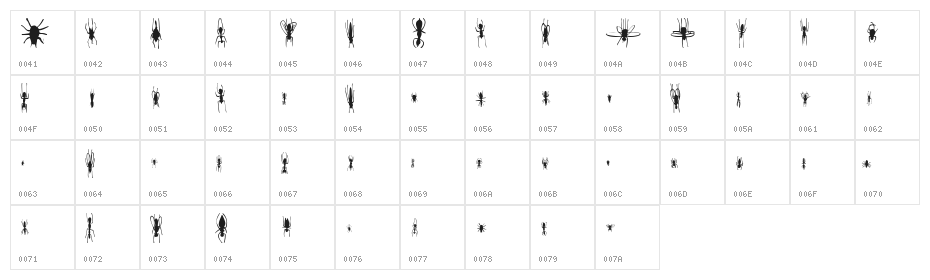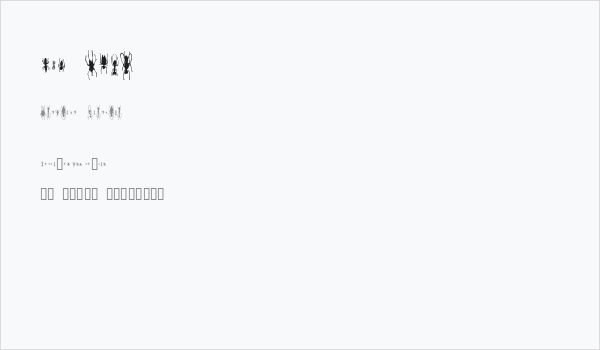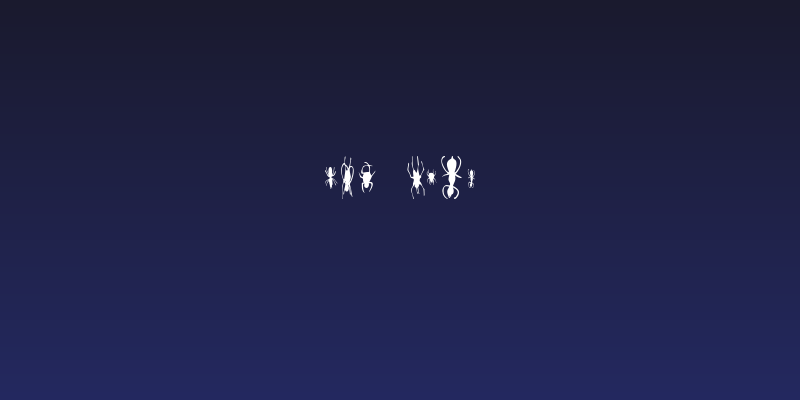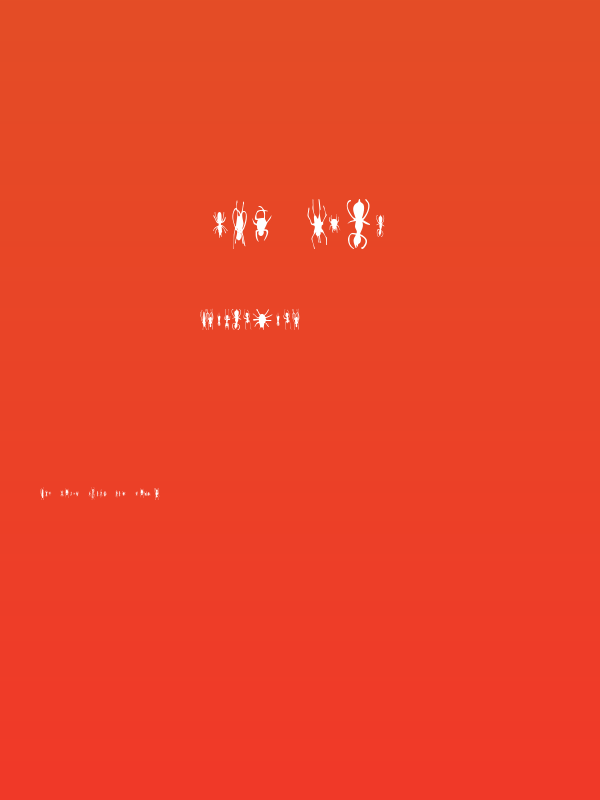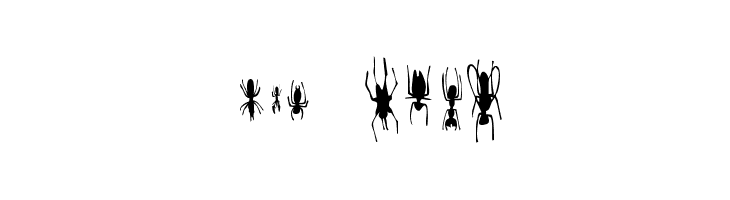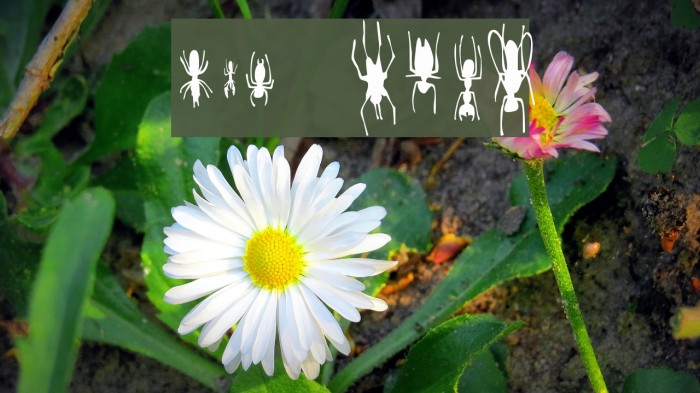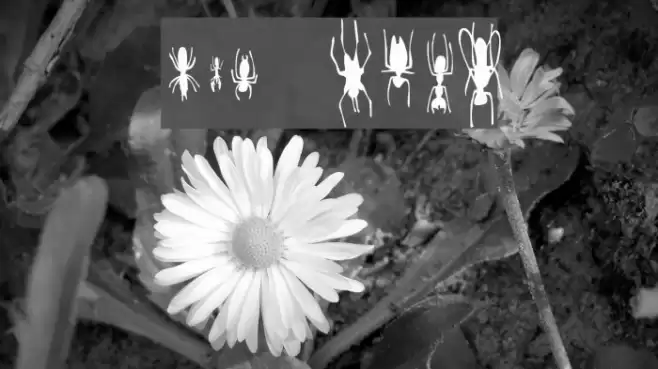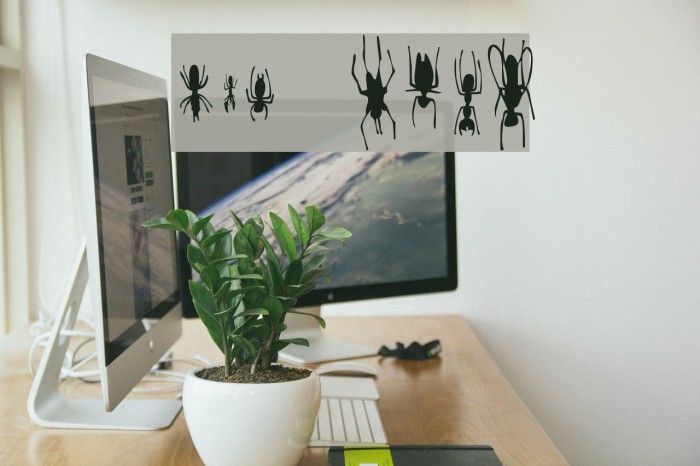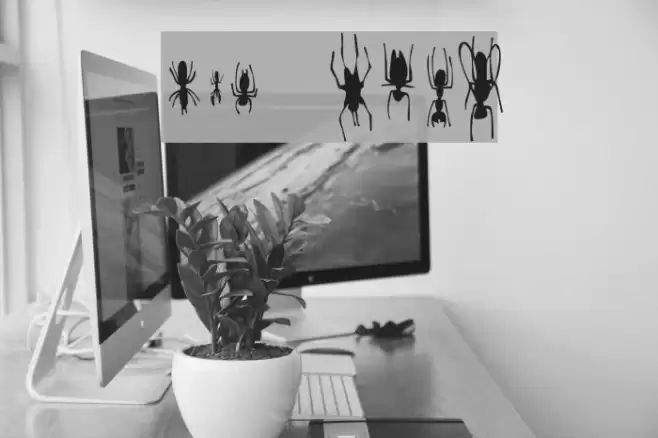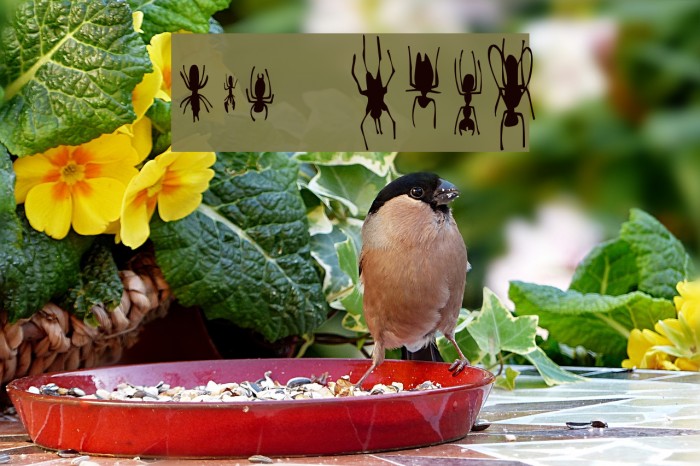
Win Bugs Font
| Estilo general | Decorative, Thematic, Organic |
| Caso de uso | Logos, Posters, Themed Headlines, Educational Graphics |
| Proyectos propuestos | Halloween designs, horror-themed posters, children's books, educational materials about insects, party invitations. |